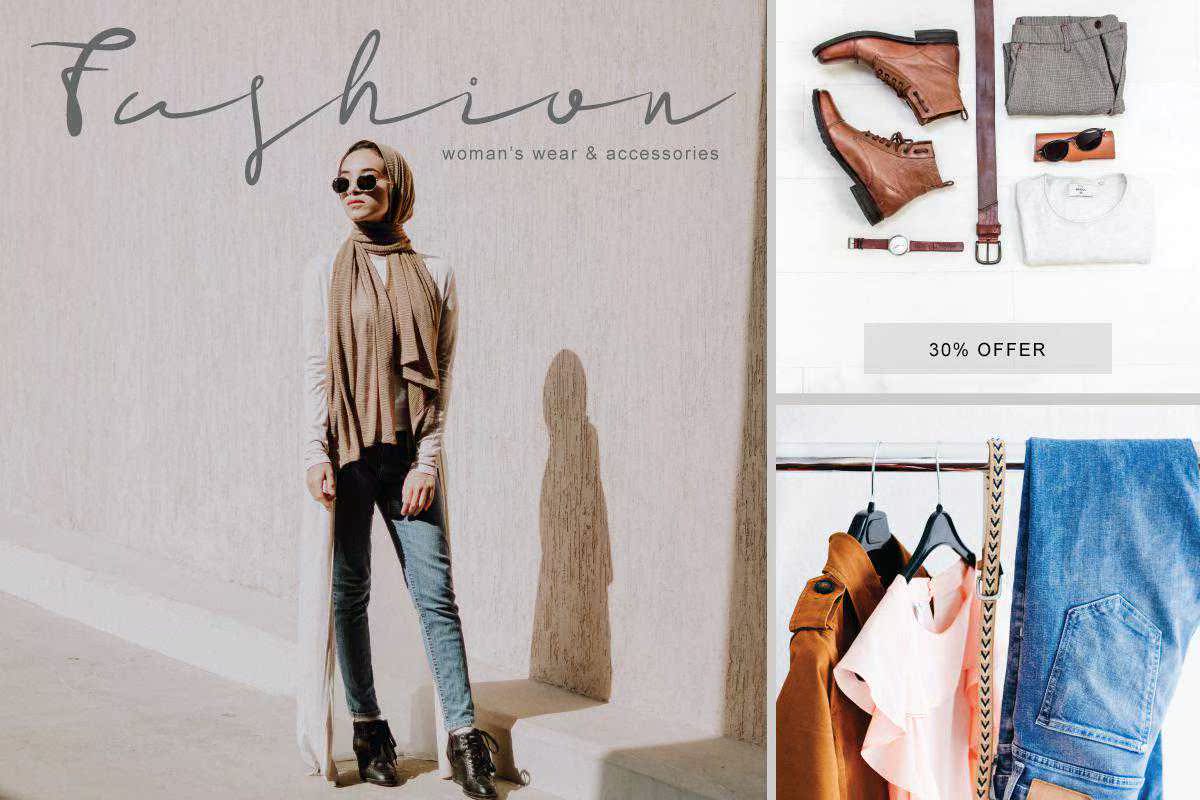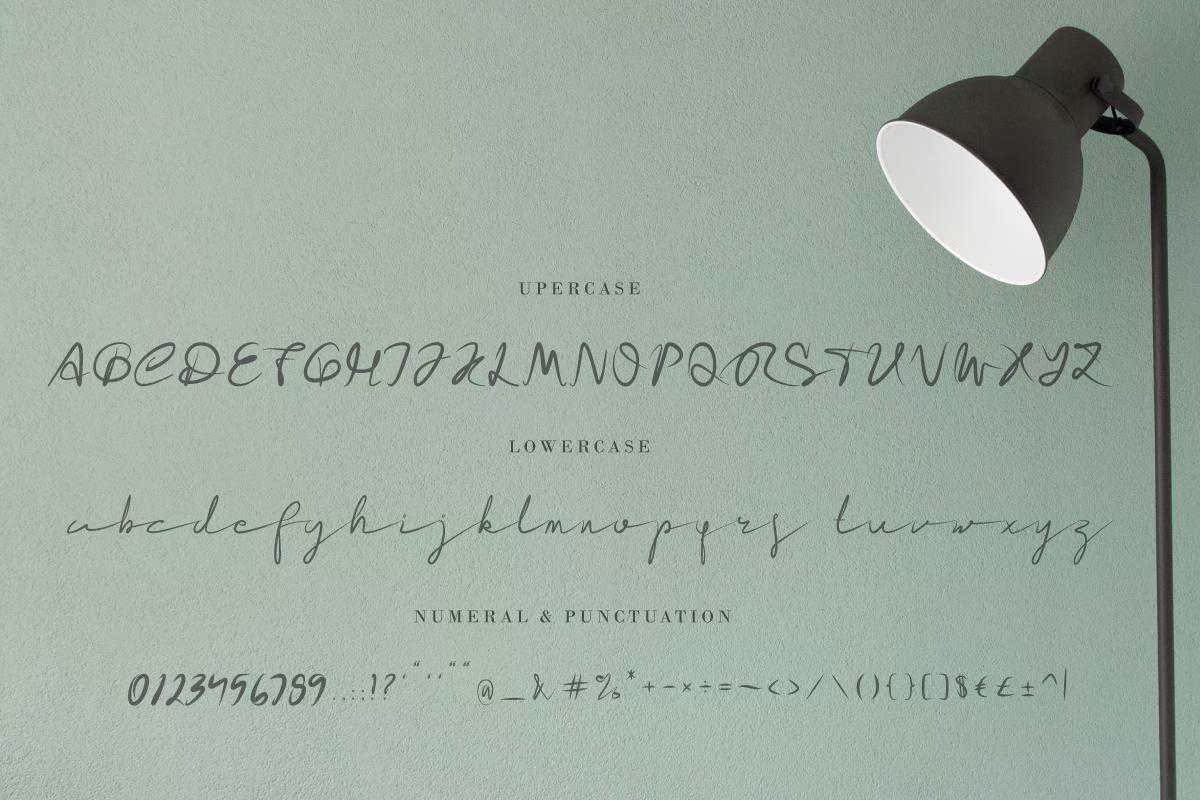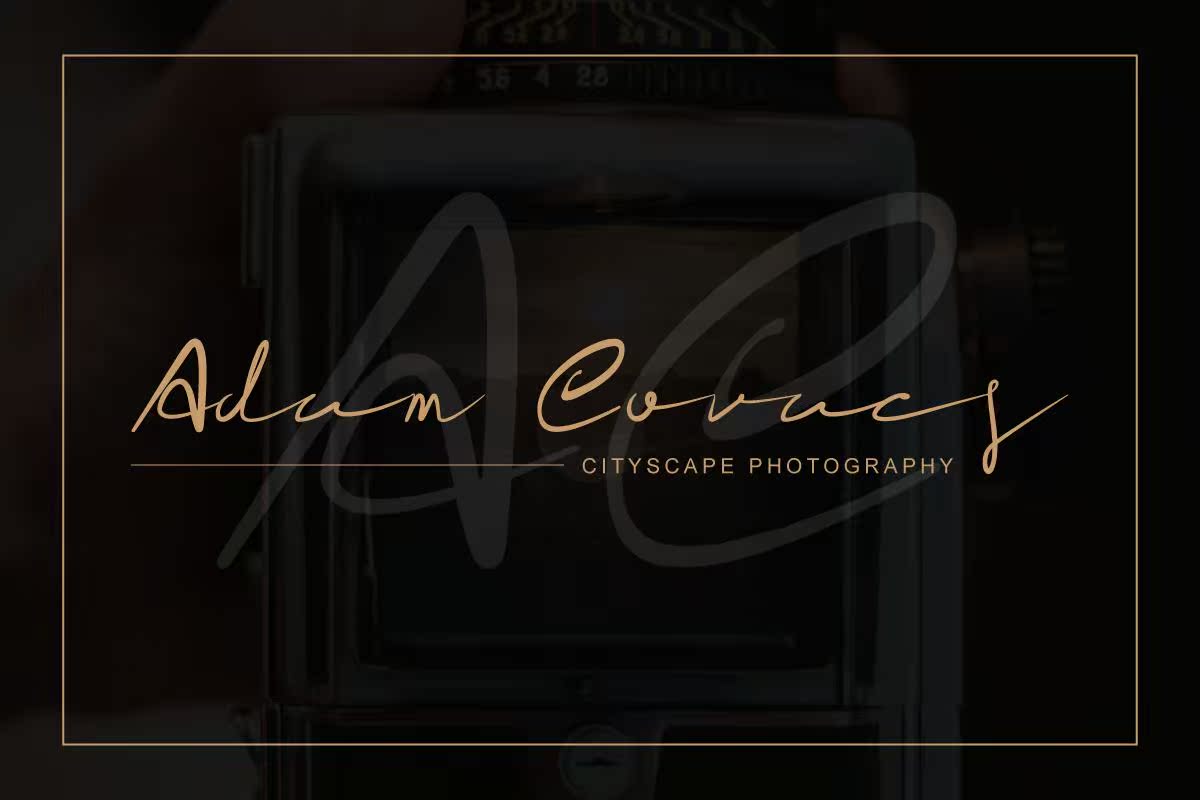
RESCUDOFFCUSIGNATURESCRIPTFONT是签名样式的手写字体,简单但仍然优雅。RESCUDOFFCUSIGNATURESCRIPTFONT可用于各种用途,如广告宣传、平面设计、印刷设计、网页设计、徽标、品牌等。RESCUDOFFCUSIGNATURESCRIPTFONT是签名样式的手写字体,简单但仍然优雅。RessCudoffcusignatures描述内容可用于各种用途,包括广告宣传、平面设计、版画设计、网站设计、徽标、品牌等。